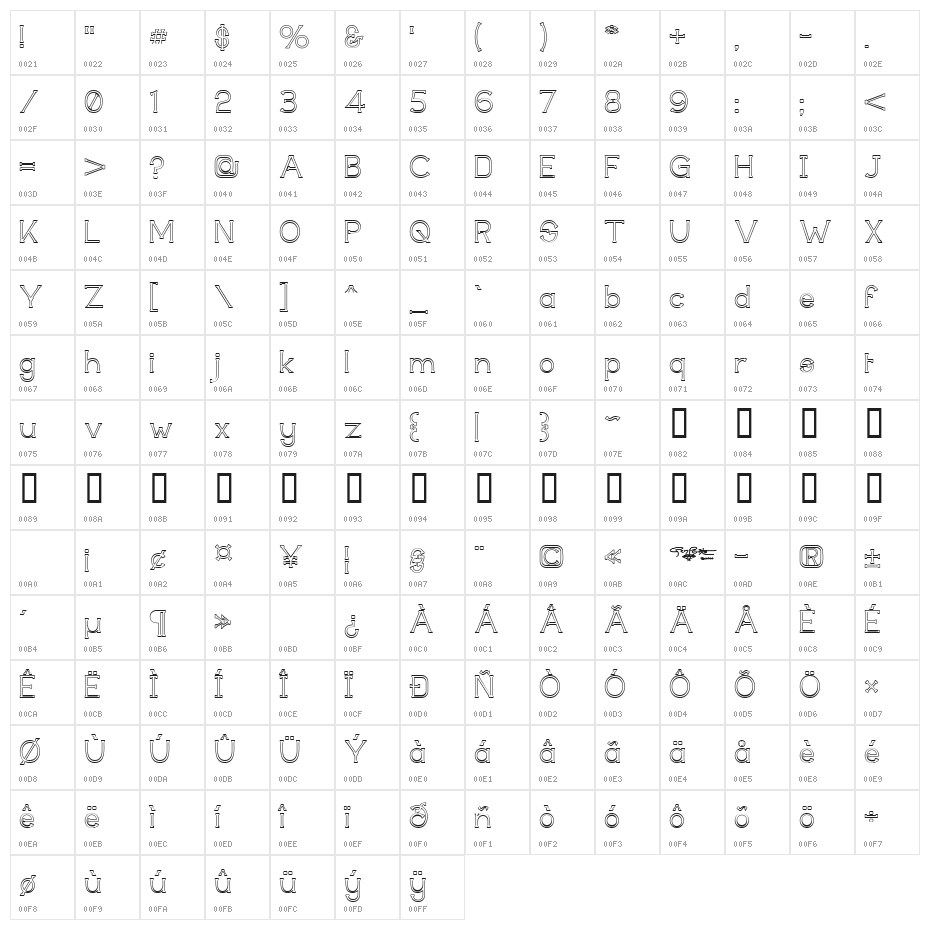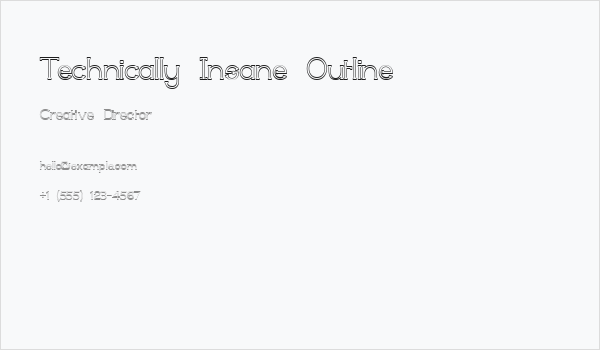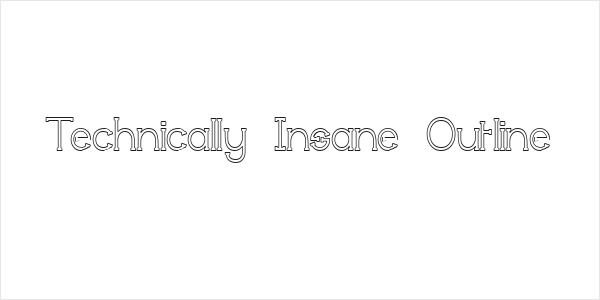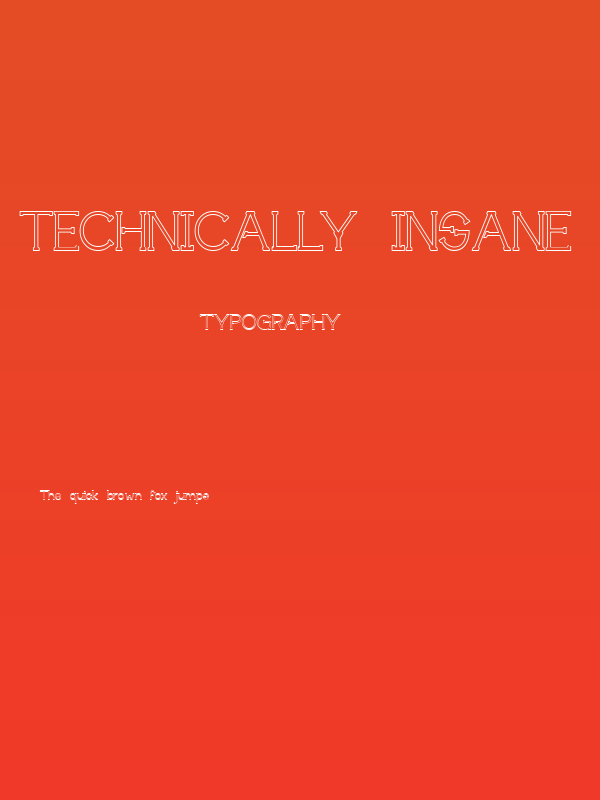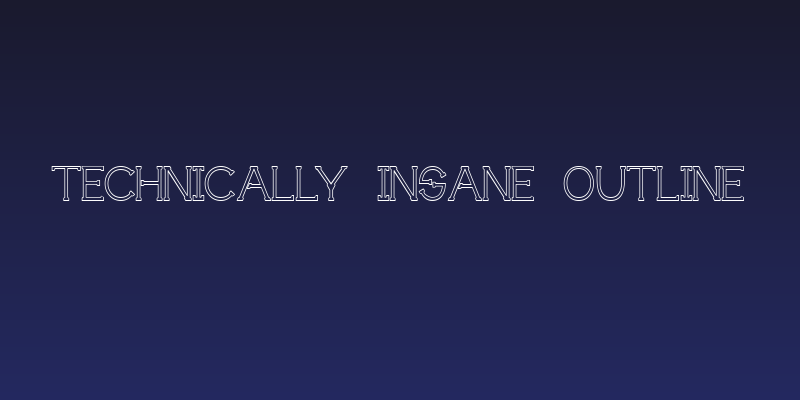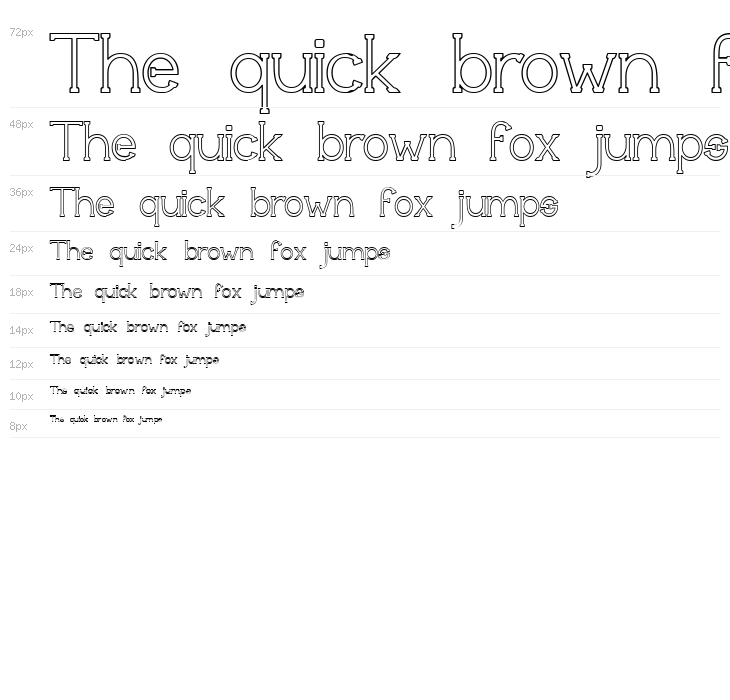
Technically Insane Outline Font
| Categorie | Outline |
| Progetti proposti | Ideal for tech-themed designs, logos, posters, and digital artwork requiring a futuristic or industrial feel. |